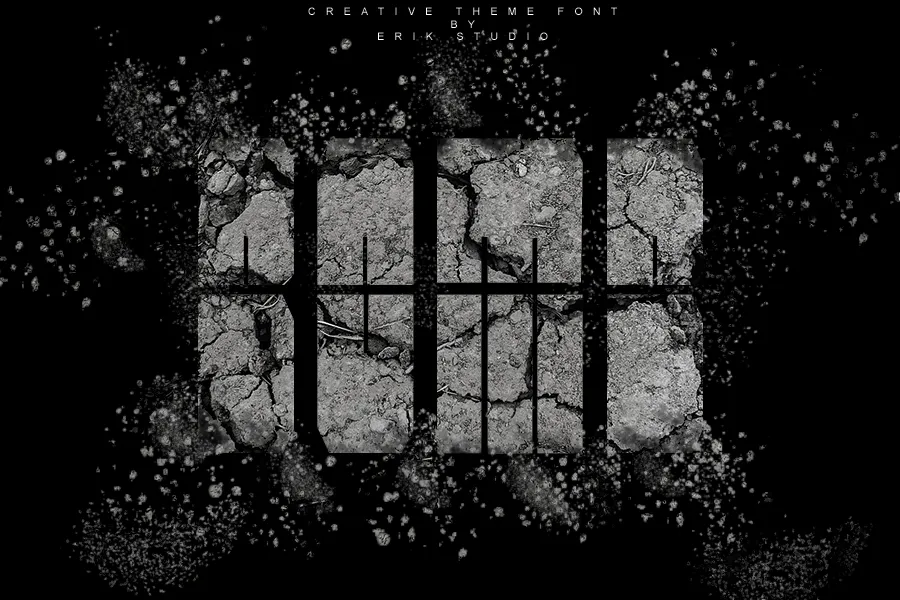
Bomb Display Font – Download Grátis
Aqui está uma descrição para a página de download da font ‘Bomb Display Font’, seguindo as orientações fornecidas: Escolha esta robusta e assertiva fonte ‘Bomb Display’ quando busca criar design gráfico poderoso. Seu estilo robusto, com um ar robotizado, irá destacar seus projetos em qualquer situação, seja para o design de logotipos ou a criação de layouts web. Tal como uma letra grossa e desafiadora, esta fonte se destaca pelo seu visual agressivo e cool. Suas linhas marcantes e suas formas assertivas criam um impacto imediato em qualquer obra que você desenvolver. Tente criar algo novo e explorar as infinitas possibilidades que este design oferece. Com ‘Bomb Display’, suas criações certamente serão inspiradoras, proporcionando uma linguagem visual robusta e atraente.